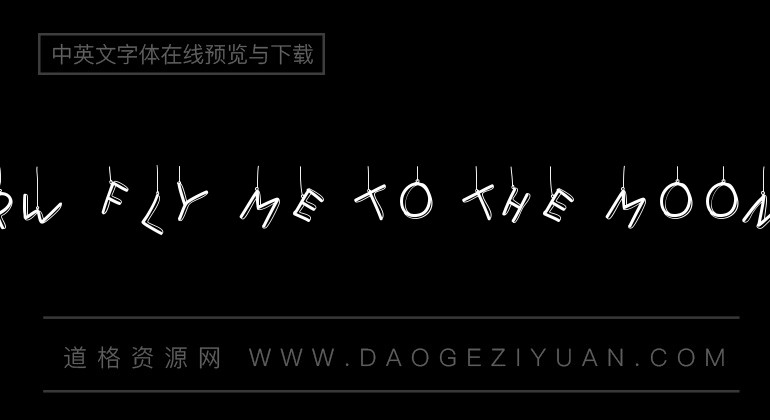
PW Fly me to the moon是一款由PW Type Foundry设计的字体,它是一款经典的未来艺术风格的字体,具有明亮而复杂的外观。它具有细节丰富的设计,可以帮助您创造出独特的文本效果。它有三种字重,每种字重都有多种字体,包括常规、斜体、粗体、粗斜体和全小写字母。它还支持多语言,可以应用于欧洲语言。内容介绍
PW Fly me to the moon是一款非常不错的手写艺术字体,具有很好的视觉感,适合于文化类的宣传设计、商业类品牌的广告和产品包装设计以及个性化文字排版等较多场景。